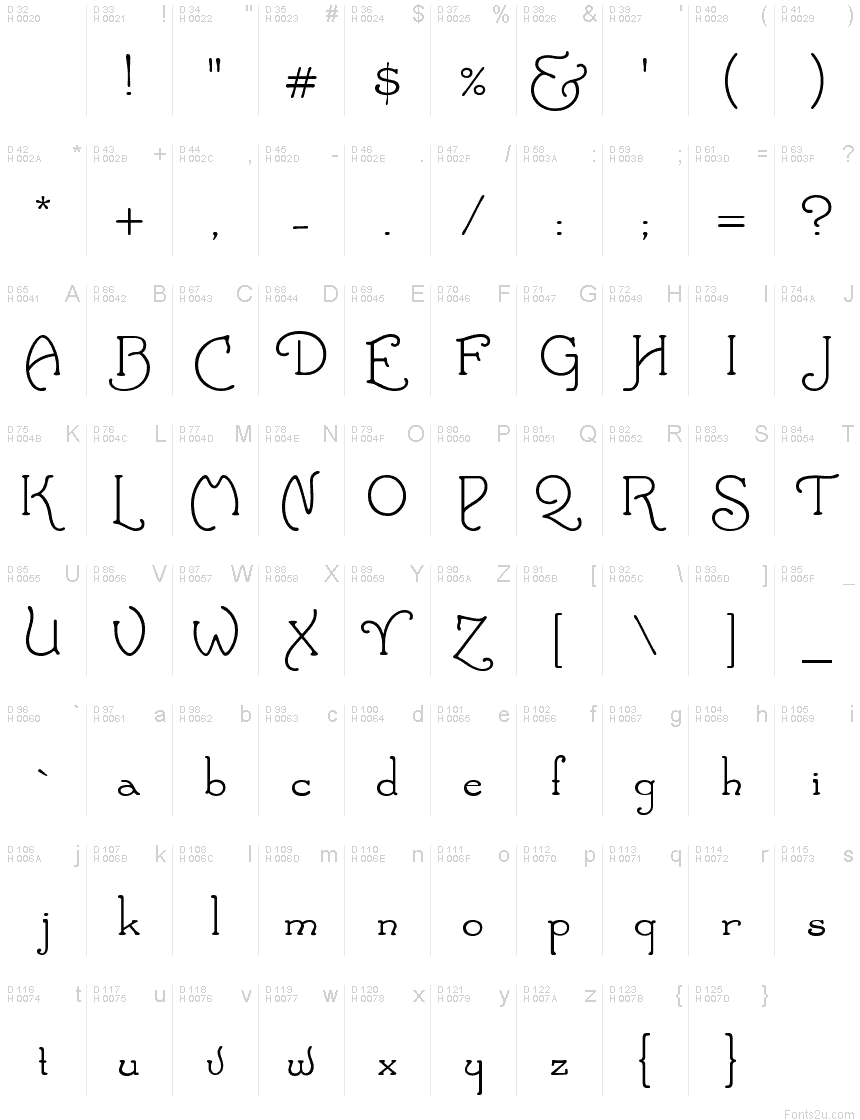
Santa's Sleigh to bezpłatny, retro krój pisma z zawijasami, który przywodzi na myśl świąteczne opowieści. Litery opierają się na pętelkowych zawijasach i miękkich, staromodnych łukach, z dużymi, ozdobnymi kapitałkami i lekkim, ręcznie kreślonym rytmem, dzięki czemu czcionka jest zabawna, ale nie przesłodzona.
To naturalny, darmowy wybór na kartki świąteczne, bileciki do prezentów, świąteczne szyldy, zaproszenia na imprezy i opakowania sezonowe, szczególnie tam, gdzie krótki tekst potrzebuje odrobiny dekoracyjności. Sprawdzi się również w tytułach, nagłówkach i monogramach, ponieważ pętelkowe kształty nadają nawet krótkim słowom charakteru wstążek lub śladów sań.
Santa's Sleigh